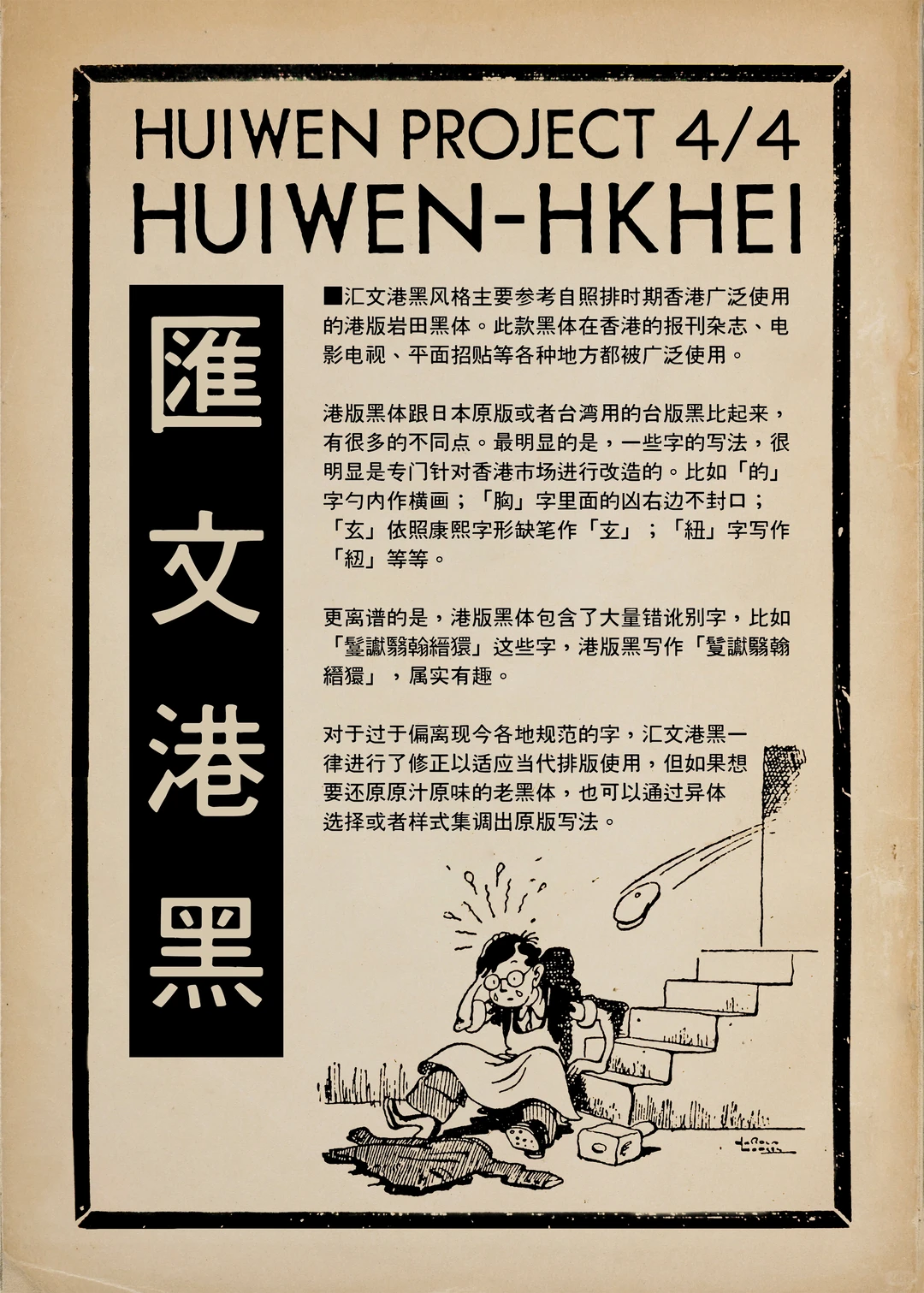
汇文港黑风格主要参考自照排时期香港广泛使用的港版岩田黑体。此款黑体在香港的报刊杂志、电影电视、平面招贴等各种地方都被广泛使用。
港版黑体跟日本原版或者台湾用的台版黑比起来,有很多的不同点。最明显的是,一些字的写法,很明显是专门针对香港市场进行改造的。比如「的」字勻内作横画;「胸」字里面的凶右边不封口;
「玄」依照康熙字形缺笔作「立」;「紐」字写作「」等等。
更离谱的是,港版黑体包含了大量错讹别字,比如「鬉讞翳翰縉獧」这些字,港版黑写作「鬘讞翳翰縉獧」,属实有趣。
对于过于偏离现今各地规范的字,汇文港黑一律进行了修正以适应当代排版使用,但如果想要还原原汁原味的老黑体,也可以通过异体选择或者样式集调出原版写法。